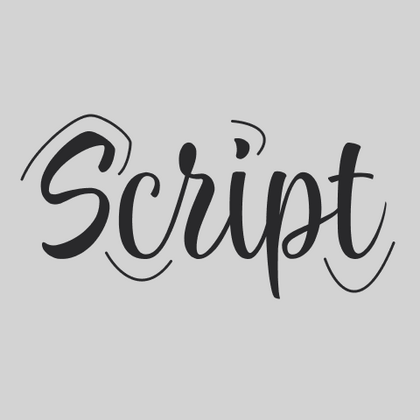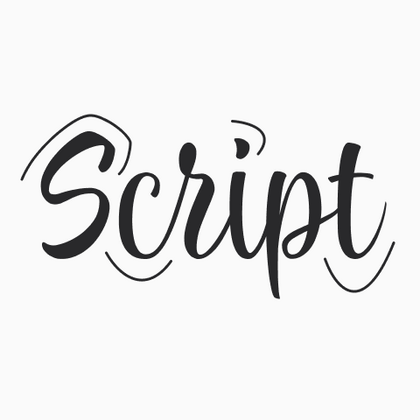
Рукописные шрифты
Эти шрифты также иногда называют сursive fonts. Они бывают наклонными и ненаклонными и выглядят так, будто кто-то написал их от руки. Однако рукописные шрифты только имитируют человеческий почерк. Их можно использовать для создания красивого и элегантного дизайна. Также они помогут придать проекту ощущение рукотворности, неформальности и теплоты. Вот примеры рукописные шрифты в разных стилях из коллекции TypeType.
Рукописные шрифты TypeType — это коллекция выразительных, динамичных и элегантных гарнитур для разных проектов.
Выберите подходящий рукописный шрифт для дизайна упаковки, создания логотипов, декоративного оформления вывесок и заголовков текста. Каждый шрифт содержит большое количество начертаний, меняя которые можно управлять характером шрифта.
TT Marks — рукописный шрифт с динамичным ритмом, тёплым характером и слегка ностальгическим настроением. Он вдохновлён классическими американскими расписанными вывесками (sign painting), которые когда-то художники создавали вручную с помощью кистей и красок. Сегодня надписи в таком стиле снова набирают популярность.
TT Disruptors — дуктальный рукописный шрифт, созданный с помощью маркера. Его рисунок уникален: потёртости, неравномерная толщина штрихов и удлинённые выносные элементы придают ему живую, динамичную текстуру и ощущение рукотворности. Характер этого шрифта своенравный и эмоциональный, но при этом тёплый и душевный.
TT Gentlemens — динамичный рукописный шрифт, в котором серьёзность и чёткость письма сочетается с элегантностью и изысканностью. У него характер и стиль настоящего джентльмена: сдержанный и всегда уместный, но при этом уверенный и эффектный.
TT Nooks является экспериментальным шрифтовым семейством состоящим из высококонтрастной антиквы TT Nooks и прямого курсива TT Nooks Script. Если бы TT Nooks была человеком (живой), то её можно было описать как элегантную даму с независимым и твёрдым характером.
TT Knickerbockers Grotesk символизирует собой монументальность, выраженную в как в традиционной исторической застройке Нью-Йорка, так и в его небоскрёбах. Энергия, постоянное движение и круглосуточная жизнь Нью-Йорка — все это отразилось в нашем TT Knickerbockers Script.
TT Berlinerins — это контрастная пара шрифтов, которая по сути является нашим трибьютом Берлину. Также, как и в самом городе переплетаются историчность и современность, так и в нашем шрифтовом семействе элегантный скрипт символизирует собой современный Берлин, а гротеск, выполненный в стиле плакатных wood-type шрифтов первой трети 20-го века, отвечает за историческую составляющую города.
Первоначально идея шрифтового семейства TT Milks заключалась в том, чтобы создать коллекцию шрифтов для использования в упаковке и брендинге молочной продукции.
TT Lovelies Script является очень живым и игривым шрифтом с небольшими нюансами непредсказуемости. В нем даже прописные буквы соединяются со строчными во всех случаях без разрывов. Каждая строчная буква имеет характерные росчерки, начинающие и заканчивающие слово.